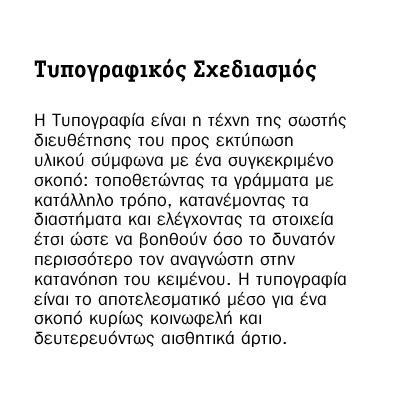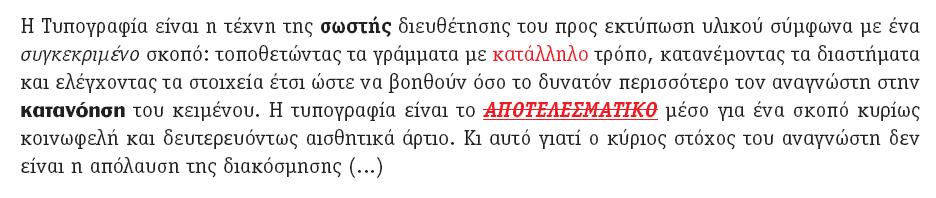
Γραμματοσειρά (font ή typeface) είναι ένα σύνολο χαρακτήρων.
2 Γραμματοσειρά (font ή typeface) είναι ένα σύνολο χαρακτήρων. Στην παραδοσιακή τυπογραφία όπου η στοιχειοθεσία του κειμένου γινόταν με μεταλλικά στοιχεία, σήμαινε ένα αλφάβητο με όλα τα συμπληρωματικά σύμβολα, σε ένα μόνο μέγεθος. Στην ψηφιακή στοιχειοθεσία είναι οι κωδικοποιημένες ψηφιακές πληροφορίες για την αναπαραγωγή του συνόλου των γραμμάτων του αλφάβητου, σε ηλεκτρονικά μέσα.
3 Μια οικογένεια γραμματοσειρών (font family) είναι ένα σύνολο γραμματοσειρών οι οποίες έχουν σχεδιαστεί πάνω στις ίδιες αισθητικές βάσεις.
4 Σήμερα, διατίθεται ένα ιδιαίτερα μεγάλο πλήθος γραμματοσειρών (σε ηλεκτρονική μορφή) με διαφορετικές αισθητικές αναφορές και χρήσεις.
5 POSTSCRIPT ή TYPE 1 Η τεχνολογία γραμματοσειρών Postscript ή Type 1 αναπτύχθηκε από την Adobe το 1985 για την χρήση σε εκτυπωτές Postscript. Κάθε γραμματοσειρά αποτελείται από δύο αρχεία: το πρώτο χρησιμεύει στην απεικόνιση της γραμματοσειράς στην οθόνη (bitmap ή screen file) και το δεύτερο στην εκτύπωσή της Ένα τρίτο αρχείο το AFM (Adobe Font Metrics) που δεν είναι απαραίτητο για την λειτουργία της γραμματοσειράς στις τελευταίες εκδόσεις των προγραμμάτων περιέχει πληροφορίες για τις διαστάσεις της γραμματοσειράς και τις αποστάσεις των γραμμάτων (spacing / kerning). Το αρχείο γραμματοσειρών Postscript περιέχει έως και 256 χαρακτήρες και δεν είναι συμβατό με το πρότυπο Unicode. Γι αυτό, μια γραμματοσειρά Postscript δεν συμπεριλαμβάνει περισσότερες από μια κωδικοσελίδες / γλώσσες (βλ. παρακάτω)
6 TRUETYPE Η τεχνολογία των γραμματοσειρών TrueType αναπτύχθηκε με τη συνεργασία της Apple με την Microsoft το Κάθε γραμματοσειρά αποτελείται από ένα μόνο αρχείο. Οι καμπύλες των χαρακτήρων ορίζουν την εμφάνισή τους τόσο στην εκτύπωση όσο και στην οθόνη. Χάρη σε μια διαδικασία που ονομάζεται hinting επιτυγχάνεται η άψογη απεικόνιση Της γραμματοσειράς στην οθόνη σε μικρά μεγέθη (π.χ. Verdana, Tahoma, κτλ.) Οι TrueType γραμματοσειρές περιέχουν περισσότερους από χαρακτήρες και είναι συμβατές με το πρότυπο Unicode. Έτσι, ένα αρχείο TrueType υποστηρίζει μια, δύο ή και περισσότερες γλώσσες.
7 OPENTYPE Οι γραμματοσειρές OpenType δημιουργήθηκαν από την συνεργασία της Adobe με την Microsoft και παρουσιάστηκαν το Στην αγορά κυκλοφόρησαν το 2000 όταν η νέα αυτή τεχνολογία άρχισε να υποστηρίζεται από τα νέα προγράμματα. Όπως και οι TrueType γραμματοσειρές, οι OpenType αποτελούνται από ένα μόνο αρχείο. Η τεχνολογία OpenType είναι συμβατή με το πρότυπο Unicode και κατά συνέπεια είναι δυνατόν να περιέχει περισσότερους από χαρακτήρες και πολλαπλές γλώσσες. Αυτό όμως που ξεχωρίζει τις γραμματοσειρές OpenType από τις TrueType είναι καταρχήν πως είναι cross-platform (σε αντίθεση με τις Postscript και κάποιες από τις TrueType γραμματοσειρές) και κατά δεύτερον, η προσθήκη ορισμένων τυπογραφικών χαρακτηριστικών (features) τα οποία ενσωματώνονται στο αρχείο OpenType.
8 OPENTYPE Αυτά τα χαρακτηριστικά μπορεί να είναι η ισοϋψής, ανισοϋψής ή σταθερού Πλάτους αρίθμηση (Lining / Old Style / Tabular), τα μικρά κεφαλαία (Small Caps), οι κλασματικοί αριθμοί (superscripts / subscripts), οι συνδυασμοί χαρακτήρων ή λιγκατούρες (ligatures), οι εναλλακτικοί χαρακτήρες (alternates) κ.α. Παράδειγμα: Fedra Sans Pro
9 To Unicode είναι ένα πρότυπο κωδικοποίησης που προτείνει έναν και μοναδικό αριθμό για κάθε χαρακτήρα. Πριν από τον την εφεύρεση του Unicode υπήρχαν εκατοντάδες διαφορετικές κωδικοσελίδες πίνακες χαρακτήρων που όριζαν μια συγκεκριμένη θέση/κωδικό αριθμό για κάθε χαρακτήρα. (π.χ. MS Windows 1253 Greek, MacOS Greek, ISO Greek κτλ.)
10 Λόγω περιορισμών μεγέθους όμως σε καμία κωδικοσελίδα δεν χωρούσαν αρκετοί χαρακτήρες. Εκτός αυτού, οι κωδικοσελίδες διαφωνούσαν μεταξύ τους ως προς τις θέσεις των στοιχείων με αποτέλεσμα να μην υπάρχει συμβατότητα μεταξύ συστημάτων ή/και λογισμικού. Το Unicode προτείνει έναν και μοναδικό αριθμό για κάθε χαρακτήρα, ανεξάρτητα από: το λειτουργικό σύστημα το λογισμικό την γλώσσα Υποστηρίζεται πλέον από τα περισσότερα λειτουργικά συστήματα, όλους τους σύγχρονους browsers και πολλά προϊόντα λογισμικού. Η εμφάνιση του Unicode αποτελεί αναμφισβήτητα μια από τις σημαντικότερες εξελίξεις στον τομέα της ψηφιακής αλλά και συμβατικής τυπογραφίας.
11 «Η Τυπογραφία είναι η τέχνη της σωστής διευθέτησης του προς εκτύπωση υλικού σύµφωνα µε ένα συγκεκριµένο σκοπό: τοποθετώντας τα γράµµατα µε κατάλληλο τρόπο, κατανέµοντας τα διαστήµατα και ελέγχοντας τα στοιχεία έτσι ώστε να βοηθούν όσο το δυνατόν περισσότερο τον αναγνώστη στην κατανόηση του κειµένου. Η τυπογραφία είναι το αποτελεσµατικό µέσο για ένα σκοπό κυρίως κοινωφελή και δευτερευόντως αισθητικά άρτιο ( )» Stanley Morison (τυπογράφος, σχεδιαστής της γραμματοσειράς Times, 1930)
12 Επιλογή των κατάλληλων γραμματοσειρών. Σχεδιασμός σελίδας ή οθόνης (μια ή δυο στήλες και παράγραφοι / στοίχιση / διαστοιχείωση / διάστιχο) Ιεραρχία πληροφορίας (hierarchy) Έμφαση πληροφορίας (highlighting) Ομαδοποίηση πληροφορίας (chunking) Legibility vs. Readability
13 Επιλογή των κατάλληλων γραμματοσειρών Όχι περισσότερες από 2 (ή το πολύ 3) γραμματοσειρές. Συνήθως μια (sans*) για τίτλους και μια (οικογένεια γραμματοσειρών) για κείμενο (serif*). Ο συνδυασμός διαφορετικών γραμματοσειρών είναι μια ιδιαίτερα δύσκολη διαδικασία που απαιτεί γνώσεις και εμπειρία.
14 Σχεδιασμός σελίδας ή οθόνης μια ή δυο στήλες και παράγραφοι Είναι ευκολότερη η ανάγνωση ενός κειμένου στο οποίο υπάρχουν 8 με 12 λέξεις ανά γραμμή. Στο διαδίκτυο είναι ιδιαίτερα σημαντικό για την αναγνωσιμότητα να υπάρχουν στενές στήλες κειμένου.
15 Στοίχιση κειμένου Κάθε ένας από τους 4 τύπου στοίχισης του κειμένου έχει θετικά και αρνητικά. Ποιος είναι καλύτερος εξαρτάται από την χρήση του κειμένου.